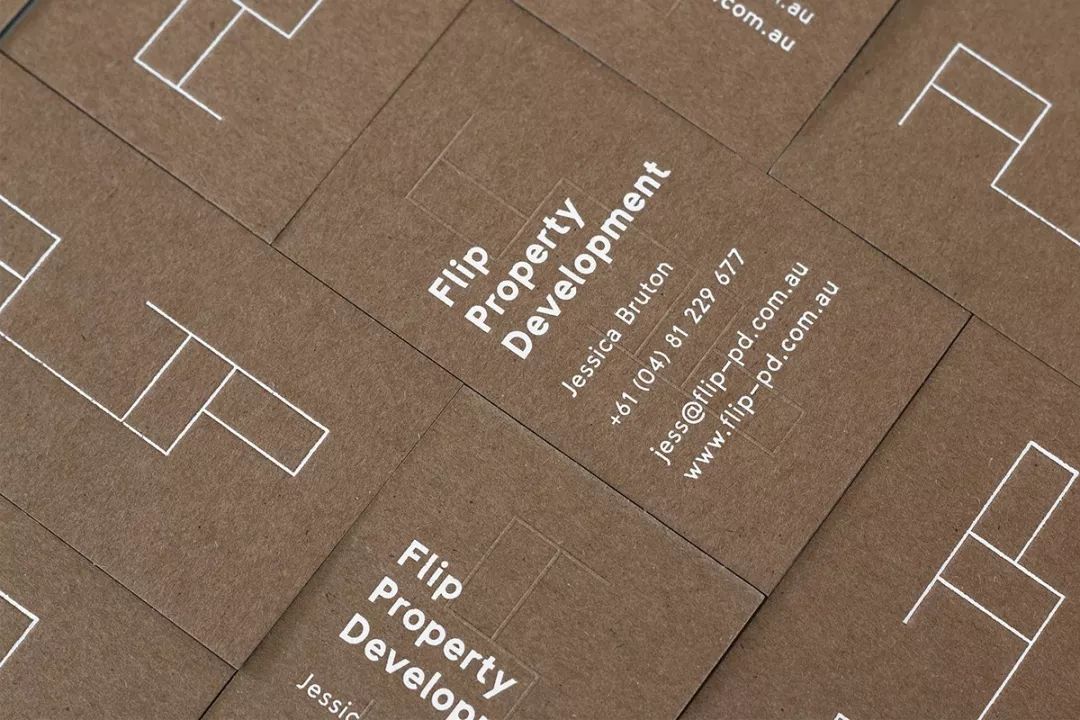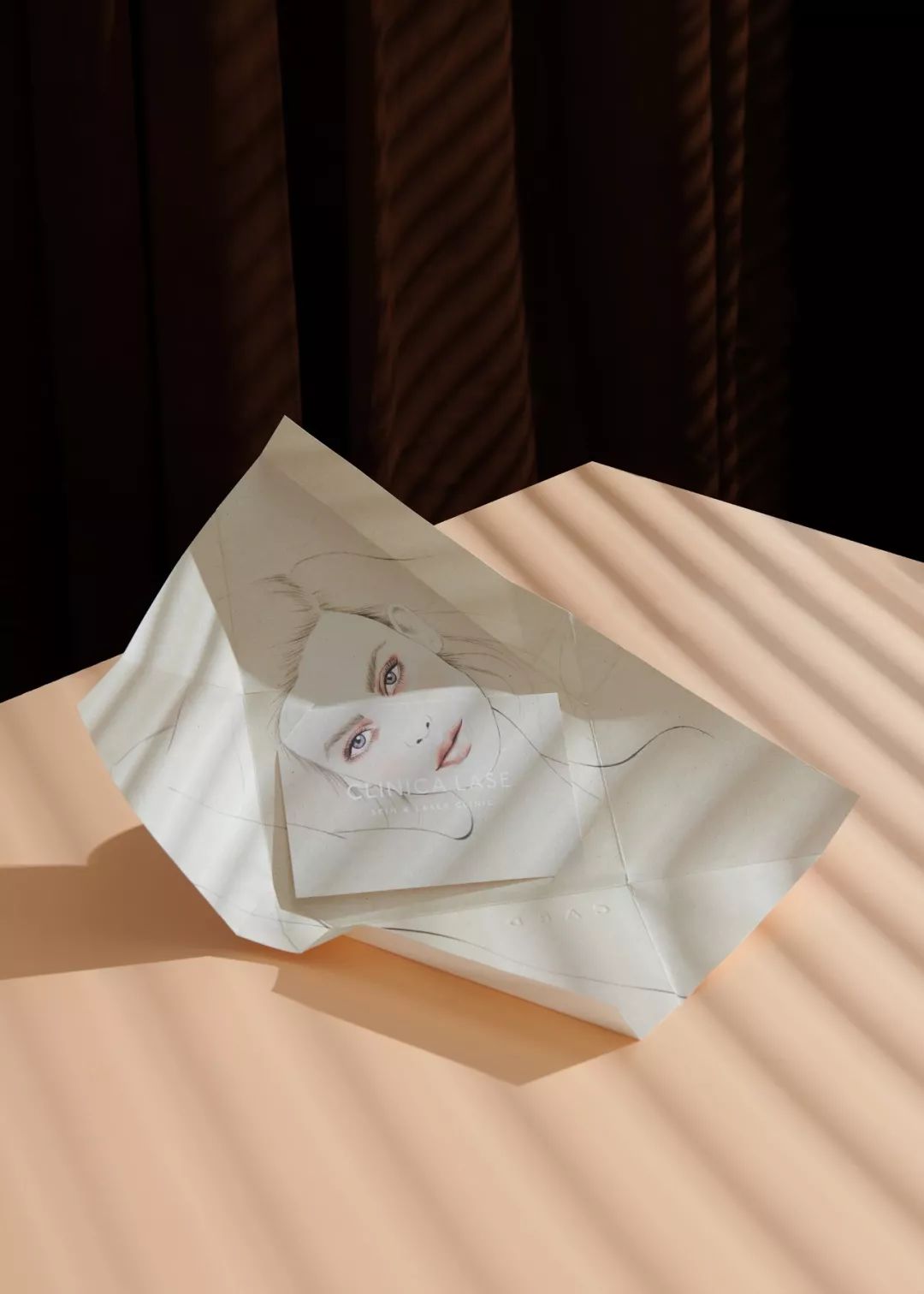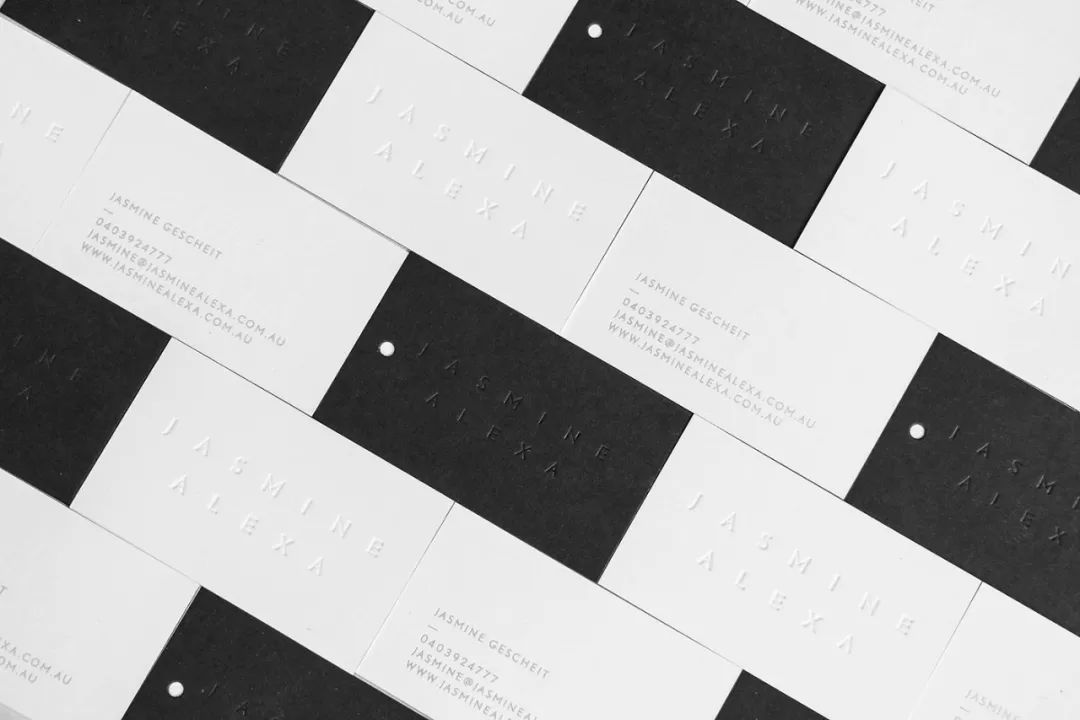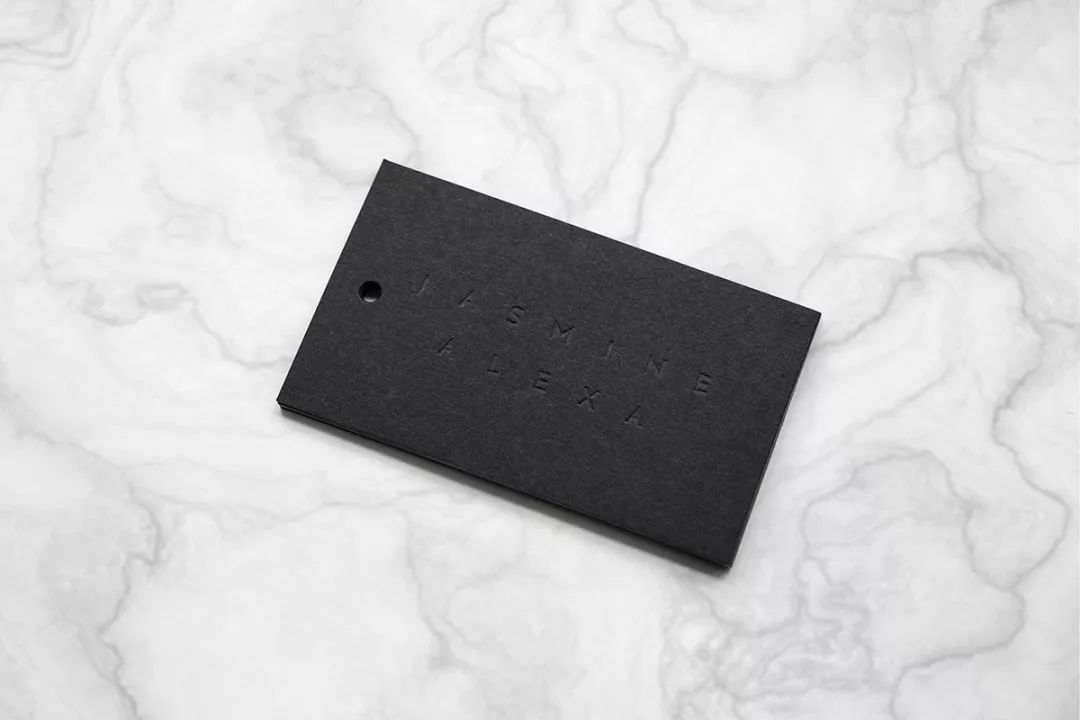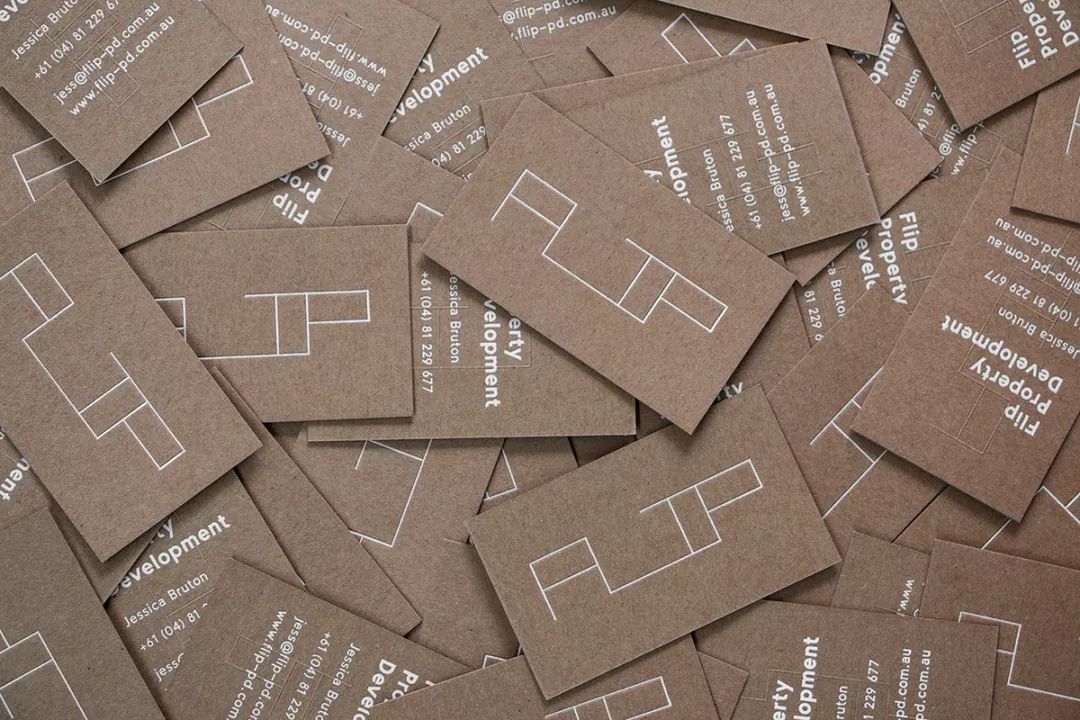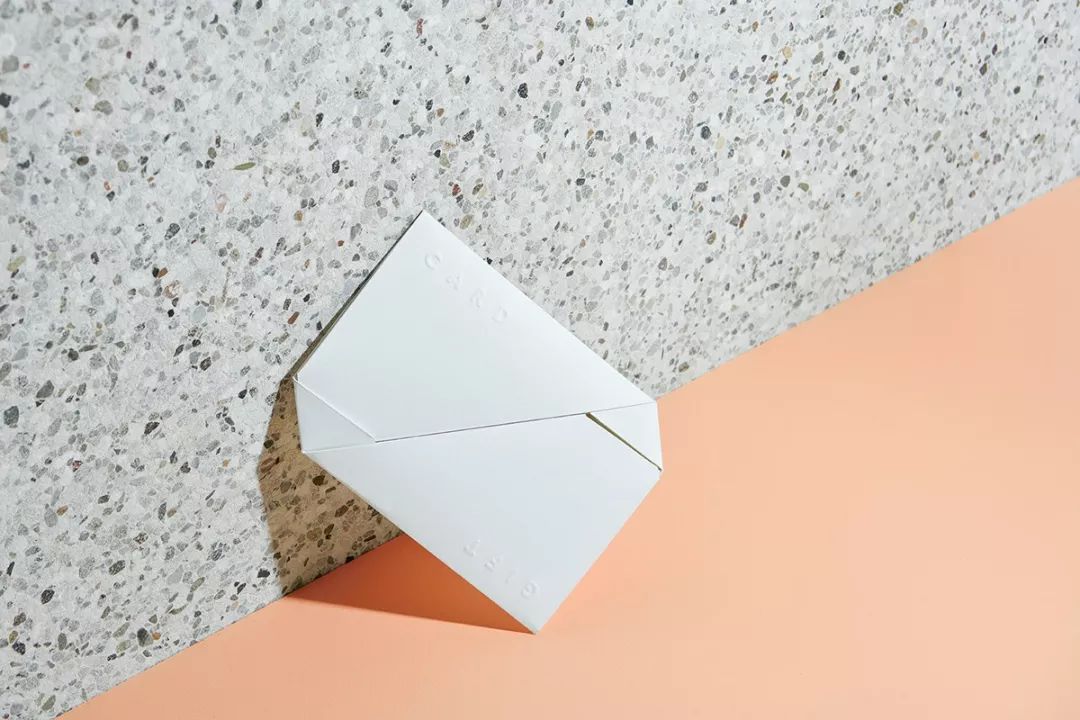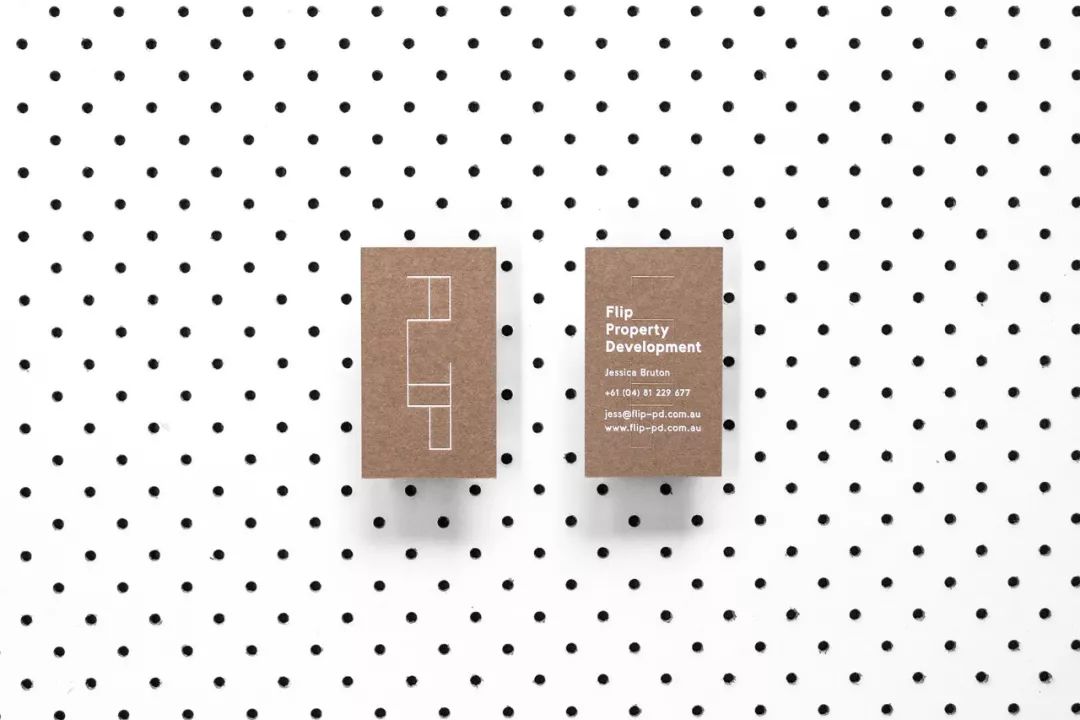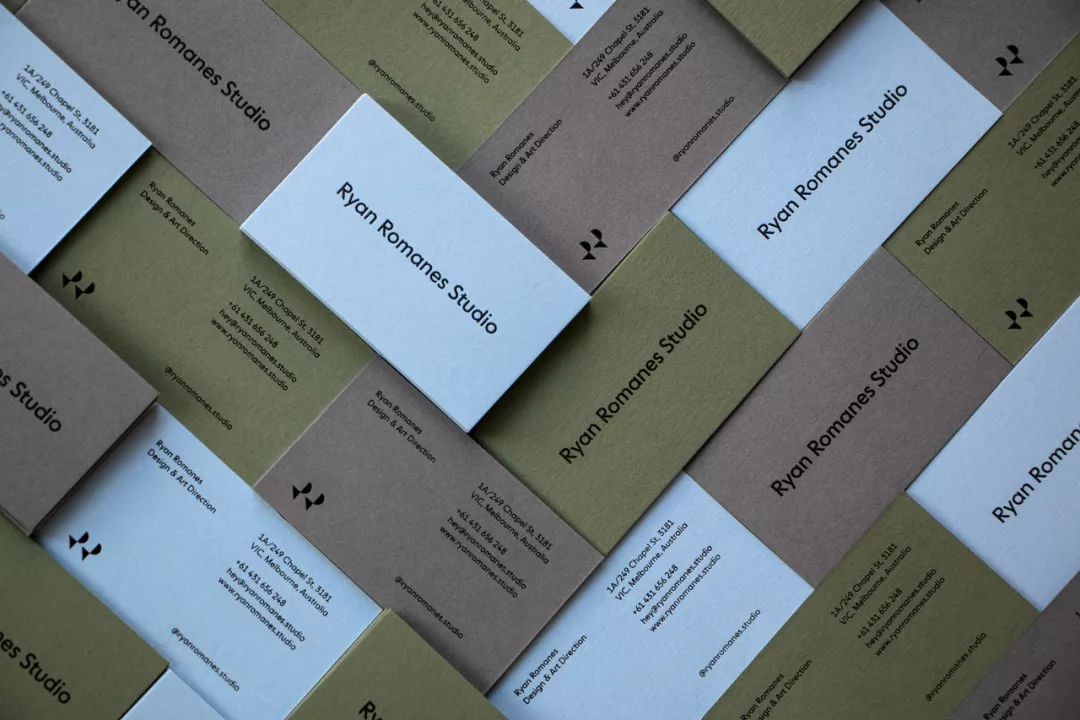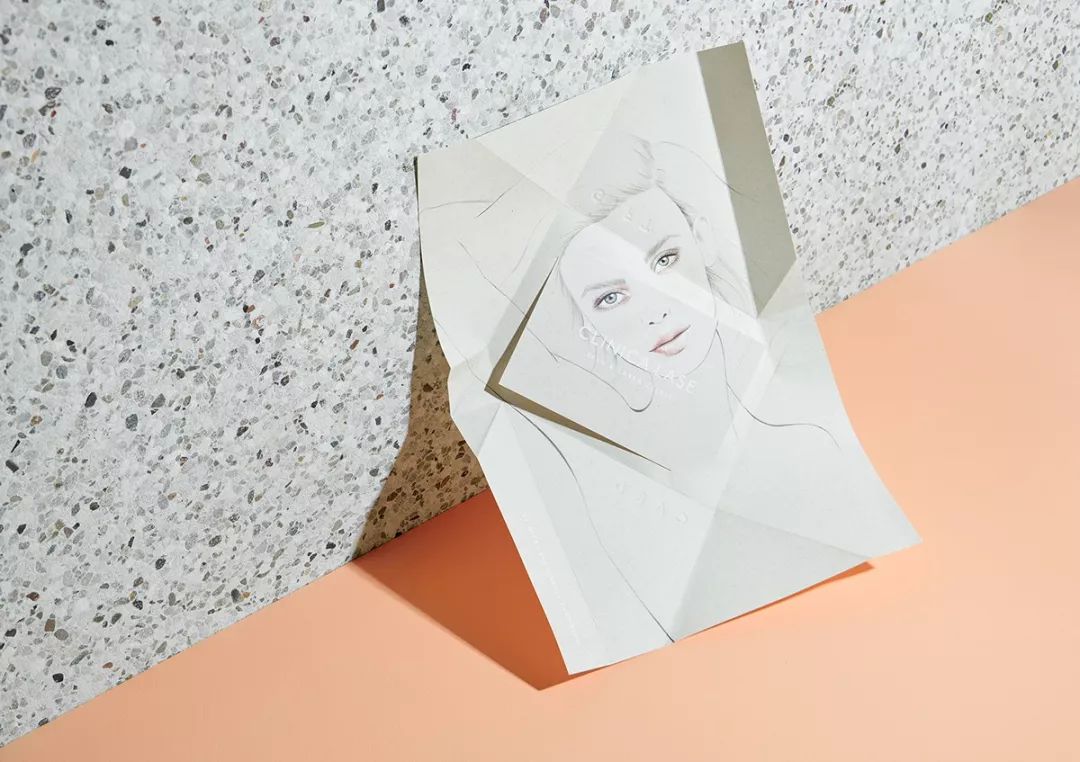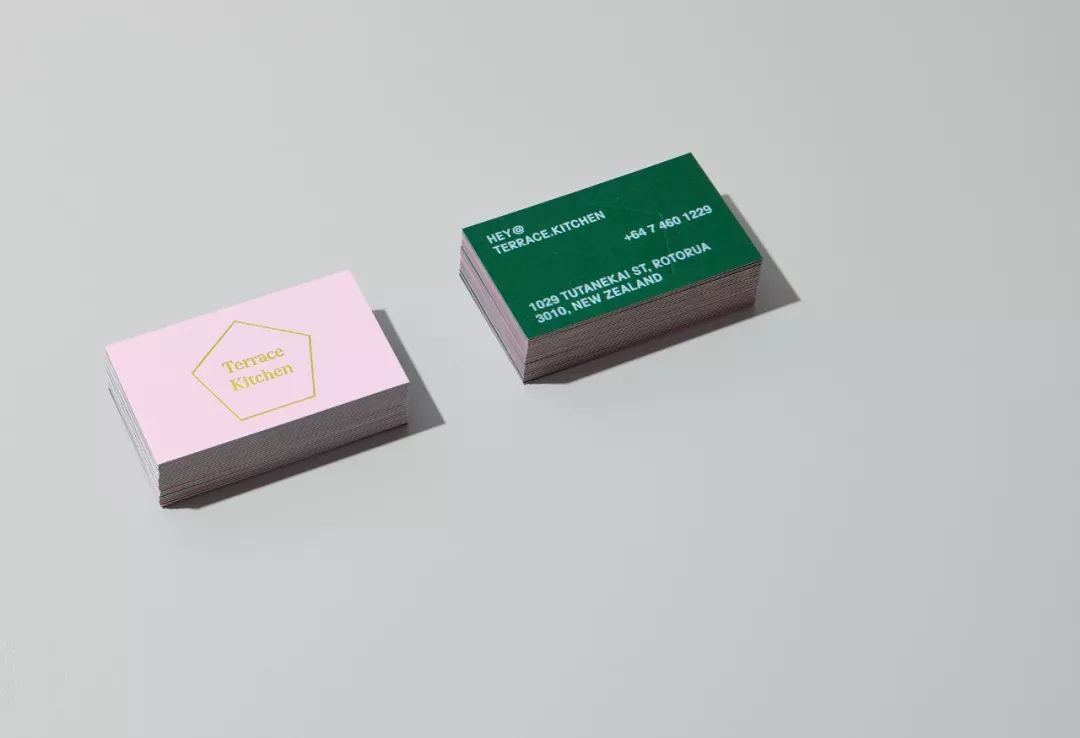
一张名片可看出一个人是否真的懂得设计
每个人都会有专属的名片,好的名片可以让你的商业精英形象愈发生动起来。它是品牌传递的重要工具,但却容易被人忽视。虽然纸质的名片几乎已被微信媒介所取代,但是作为设计师更不应该放弃这种貌似不重要的设计。
越简单的设计,更考验设计能力。一张名片可看出一个人是否真的懂得设计,因为里面包含太多基本功了。如果连一张简单的名片都做不好,更不要说其他的设计了。甚至现在一些广告设计公司招聘设计师,面试就很简单,要求你设计一张名片即可。
看看澳大利亚 Ryan Romanes Studio 设计工作室的名片设计作品:
一张设计精美的名片可以玩转品牌。不妨使用大胆的图片色彩、独特的形状字体来表现品牌的创造力、艺术性和趣味。
对于许多商业名片设计而言,最大的挑战是如何打破常规,而不只是设计一张普通的名片。例如镂空。
金属油墨、烫印铝箔、局部光油在细节上的处理都能够让你的名片脱颖而出。在保持简洁的外观同时,提升了优雅的格调,令人印象深刻。
展示了铝箔烫印和凹陷的纹理凹陷的魅力
看一个 Neilsons 品牌案例:
Personal Business Cards
顺带和大家说说,设计一张名片时,需要了解哪些基本的设计参数。
尺寸
最常见的商业名片尺寸是 84mm*55mm,或 3.5英寸*2英寸。值得注意的是:任何非典型的尺寸可能会花费更多的预算。
材质
虽然大多数名片是纸质的,还会有更多的选择,比如塑料、木材、金属甚至石板。
储存
为了获得最佳质量和清晰的外观,设计应保存为基于矢量的PDF,而不是JPEG或PNG。
字体
选择正确的字体绝对是加分项~记住以下这些原则:
1、确保最好是要大于8号字体,增加可读性。
3、使用装饰性或脚本字体要谨慎,千万别为了追求好看的字体而影响可读性。
4、和设计师确认使用的这款字体得到版权许可。
以上是一些名片设计的技巧和规范,希望能给大家带来帮助。
对于客户而言,一张设计精良的名片能够让客户保持良好而持久的印象,这就是为什么名片设计如此重要。对于设计师来说,如果一个设计师对印刷工艺不够了解的话,那么作品落地时必将大打折扣。建议设计师们都抽空学些最基础的印刷知识,相信对你是有帮助的。